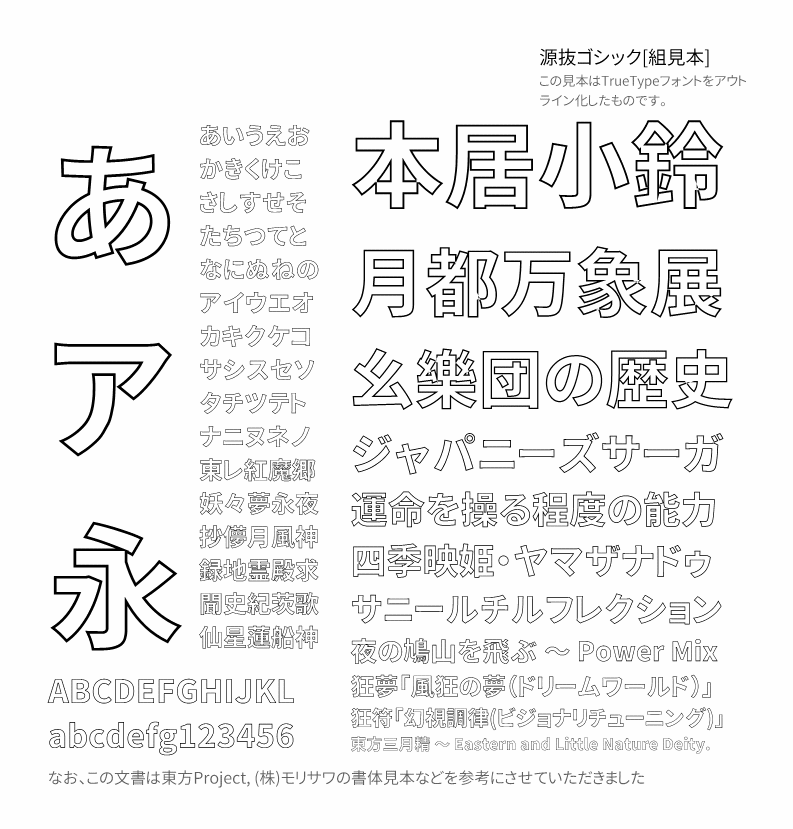
源拔黑体(日文名:源拔ゴシック)是基于Genshin Gothic P Heavy版本通过Fontforge软件添加的轮廓处理而成的字体。
制作这款字体的初衷是,即使很难通过绘图或写字板等软件处理轮廓,您也可以轻松创建带有轮廓处理的设计。
这个概念可能类似于森泽的“Shin Go Shadow”或 Type Lab 的“Anito Inline”。